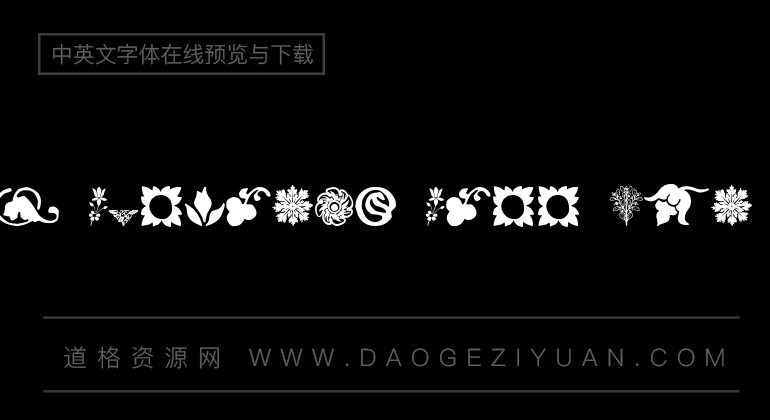
Rough Fleurons Free Two Font
Rough Fleurons Free Two Font是一种免费的装饰性字体,它由设计师Gemma O'Brien创建。该字体包含了许多花卉和叶子的图案,这些图案可以用来装饰文本。它的风格非常独特,带有手绘和粗糙的感觉,因此非常适合用于书籍、海报、卡片、标志和其他创意设计项目。这个字体有两种版本,一个是带有纹理和细节的版本,另一个是纯粹的版本,适合不需要粗糙纹理的场合。该字体支持多种语言,包括英语、西班牙语、法语、德语、意大利语和葡萄牙语等。
Rough Fleurons Free Two Font是一款非常不错的手写艺术字体,具有很好的视觉感,适合于文化类的宣传设计、商业类品牌的广告和产品包装设计以及个性化文字排版等较多场景。